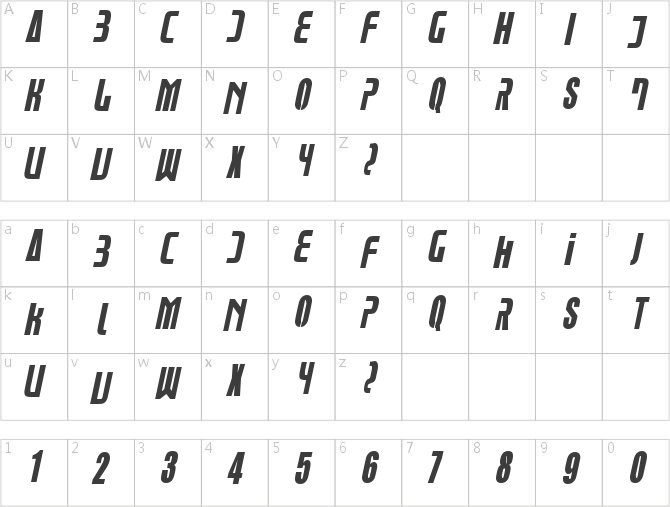
Glue-Klinging-Klan-Thin-Italics 詳情頁(yè)
Glue-Klinging-Klan-Thin-Italics
Glue-Klinging-Klan-Thin-Italics字體字庫(kù)是一款讓人賞心悅目、百看不厭的英文字體,適合各類廣告和產(chǎn)品包裝設(shè)計(jì)應(yīng)用,字體大小0.02MB,格式為ttf字體,上傳用戶是/zyj【GF】,作者/版權(quán)方為未知